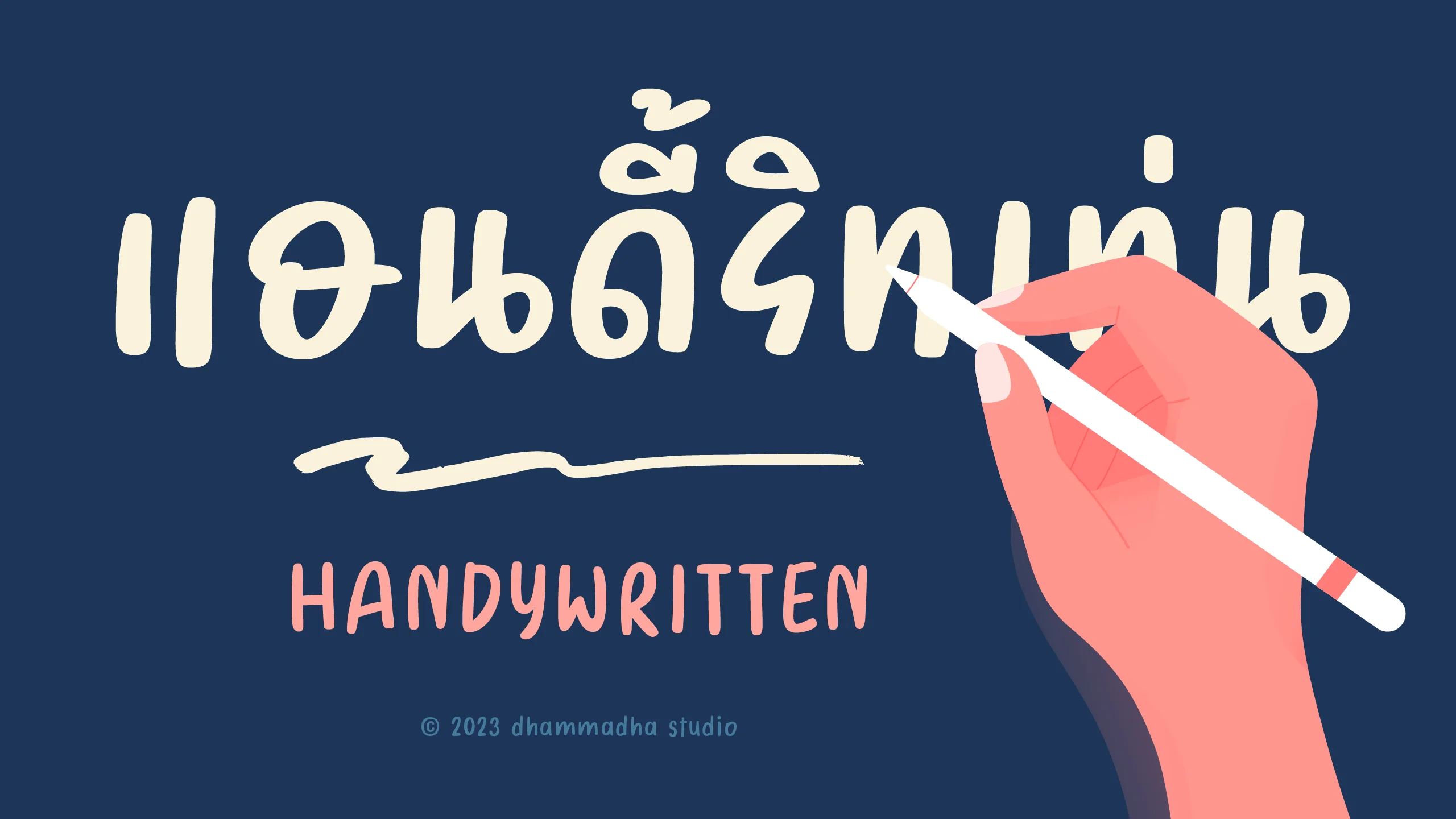
HANDYWRITTEN
การกลับมาอย่างยิ่งใหญ่ในฐานะ REMAKE PROJECT II ที่นำเอาฟอนต์ลายมือสุดฮิตในใจใครหลายคนอย่าง "แฮนดี้ไรท์" มาทำการสังคายนาและพัฒนาขึ้นใหม่ทั้งหมด เราตั้งใจรักษาเสน่ห์ของลายเส้นที่เป็นมิตรและดูเป็นกันเองเอาไว้อย่างครบถ้วน มอบบรรยากาศที่ดูผ่อนคลาย สบายตา และเข้าถึงง่ายเหมือนลายมือเขียนจริงๆ ที่มีความน่ารักแฝงอยู่ในทุกตัวอักษร เหมาะสำหรับการสร้างสรรค์งานดีไซน์ที่ต้องการความอบอุ่นและเป็นกันเองกับผู้อ่าน ในเวอร์ชั่น "HANDYWRITTEN" นี้ เราได้อัปเกรดขีดความสามารถแบบก้าวกระโดดเพื่อให้ตอบโจทย์การทำงานระดับสากลมากยิ่งขึ้น ทั้งการปรับปรุงโครงสร้างอักษรให้มีความสมดุลและอ่านง่ายขึ้นในทุกขนาด ไปจนถึงการจัดระเบียบช่องไฟและจังหวะของสระวรรณยุกต์ให้มีความประณีตและแม่นยำสูงสุด ไม่ว่าจะเป็นงานคอนเทนต์ออนไลน์ สื่อสิ่งพิมพ์ไลฟ์สไตล์ หรือการจัดวางข้อความสั้นๆ บนสินค้า ฟอนต์ชุดนี้จะช่วยให้งานของคุณดูมีชีวิตชีวาและมีความเป็นธรรมชาติที่ทันสมัยขึ้นอย่างชัดเจน